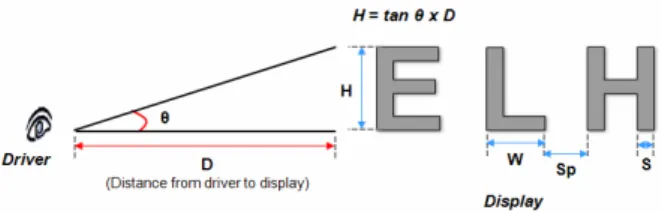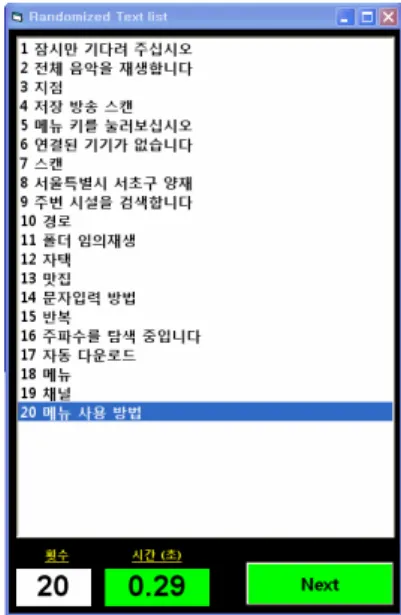
What are Legible Korean Font Sizes within In-Vehicle Information Systems?
ABSTRACT
Objective: The aim of this study is to determine legible Korean font sizes within in-vehicle information systems(IVISs) in diving conditions. Background: Font legibility within IVISs is one of important causes on its' safe operations during driving.
Several researches proposed some guidelines on the legible English font sizes within IVISs. On the contrary, appropriate Korean font sizes have been hardly known in spite of the typological differences between English and Korean. Therefore, more systematic researches for improving the legibility on Korean font size within IVISs have been required. Method: In this study, an experiment was performed with the following experimental factors: the existence of vibration, the color contrasts(white on black, black on white), the font types(HDR, CubeR, Gothic), and the font sizes(6, 8, 10, 12, 14, 16, 18, 20, 22, 24pt). To fit the experimental conditions into real driving environments, the illuminance was controlled to 15lx by using LED lamp and the distance between IVIS and participants was kept to 70cm. Moreover, all participants took the shutter glasses for employing well-known occlusion techniques. Results: The experimental results showed that 'HDR' and 'Non-vibration + Black on white' group took the shortest response time, and decreasing slopes of the response time with increasing font sizes were slowing down at 14pt then flattened out at 22pt regardless of the existence of vibration and color contrasts. Conclusion: The minimum size for legible Korean font would be about 14pt(5.47mm) and the optimum size would be about 22pt(8.59mm). Application: The guideline on the Korean font sizes from this study will be applied to design an IVIS in the future.
1. Introduction
2011년 현재 국내 내비게이션의 누적 판매량은 약 800 만 대로, 차량 등록대수 대비 약 50% 수준이라고 한다 (iNews24, 2011). 일본의 경우, 내비게이션 보급률이 전체 등록 차량 대비 80%여서 국내에서도 점점 더 보편화되리라
예상된다. 최근 보급되는 내비게이션들은 길안내 시스템뿐만 아니라 음악/동영상 재생, DMB 시청, 게임 등의 엔터테인먼 트 기능까지 갖추고 있다. 또한 이러한 기능들은 자동차 내 공조시스템이나 제어시스템과 통합되고 스마트폰과 연계되 는 추세여서 자동차 내의 정보시스템(IVIS: In-Vehicle Information System)은 점점 더 복잡해지고 있다. 이러한 복잡성 증대는 사고를 유발하는 매우 중대한 요인 중의 하나
인 운전 중 IVIS 조작의 위험성을 더욱 부각시킬 것이다.
운전 중 운전자가 얻는 피드백의 90%는 시각적인 정보이 다(Bach et al., 2009). Lee et al.(2010)에 따르면 내비게이 션 이용 중 사고에 가장 큰 영향을 끼치는 것은 아이콘과 텍 스트의 가시성이라고 한다. 즉, 아이콘과 텍스트가 눈에 잘 보이지 않으면 그 정보를 획득하기 위해 운전자의 시선이 IVIS에 오래 머물고 이는 중대한 사고로 이어질 수 있다는 것이다. 이 때문에 많은 자동차 관련 설계 가이드라인들은 운전자의 시선이 운전 외 정보에 오래 머물지 않도록 IVIS 를 설계해야 함을 강조하고 있다(ISO15005, 2002; TRL, 2002; JAMA, 2004). 운전자들은 운전 중 응시시간이 0.8 초보다 짧고, 응시 사이 간격이 3초 이내이면 안전하다고 느 낀다(Green, 1999). Zwahlen et al.(1988)은 안전 상의 이 유로 운전자들은 2초 이상 운전 태스크로부터 분산되면 안 된다는 것을 보였다. 또한, ISO15005(2002)에서는 시선이 IVIS에 머무르는 시간(도로 외 시각주의 시간, eyes-off- the-road-time)이 1.5초보다 길지 않도록 권고하고 있다.
화면 상의 시각적인 정보는 이처럼 짧은 시간 내에 운 전자에게 정확하게 전달되어야 하므로 텍스트의 가시성 (Visibility), 가독성(Legibility), 이독성(Readability)을 확 보하기 위한 노력이 IVIS 설계에서는 특히 중요하다. 가시성 은 문자나 아이콘이 주위와 구별되게 하는 성질을 의미한다.
이에 반해 가독성(legibility)이란 글자가 잘 읽히는 정도를 의미하며(Won, 2004), 글자나 단어, 기호 그리고 본문에 있 어서 타이포그래피(Typography)의 요소를 통합하고 조정 하는 것을 말한다. 일반적으로 가독성에 영향을 미치는 요인 으로는 글자체, 글자크기, 획폭, 글자/줄간격, 글자색/배경색 대비, 시야거리, 조도 등과 같이 다양하다(McLean, 1965;
Vartabedian, 1971; Vanderplas and Vanderplas, 1980;
Hwang et al., 1997; Beranard et al., 2003; Lee et al., 2007). 이독성은 문자에 의해 표현되는 단어, 문장, 문단의 정보내용을 이해 가능하게 하는 속성으로 각 문자의 글자체 보다는 자간간격, 문자의 연결, 줄간격, 여백 등의 문장구조 와 내용에 많은 영향을 받는다(Jung et al., 2006; Chae et al., 2007).
운전 중에는 운전자가 IVIS에 지속적으로 초점주의 (focused attention)를 줄 수가 없고 분산주의(divided attention)에 의존해야 하며 조도가 불연속적으로 변경되며 진동에 의한 화면 떨림이 있는 등 특히 가독성을 해칠 수 있 는 환경이다. 운전 환경에서의 적절한 가독성을 보장하기 위 해서 여러 가이드라인들에서 영문에 대한 글자크기 가이드 를 제시하고 있으나 한글에 대해서는 아직 적절한 가이드가 부족하다. 영문에 비해 한글은 획수가 많고 복잡한 구조를 갖기 때문에(Hwang et al., 1997) 적절한 가독성을 보장하 는 크기에 대한 기준이 다를 가능성이 크다. 따라서 본 연구
에서는 운전 환경에서의 적절한 가독성을 보장하기 위한 IVIS 내 한글 글자크기를 실험을 통하여 도출하였다.
2. Research Backgrounds
2.1 English font size within IVIS
Green(1999)은 IVIS 내의 글자크기에 대해 텍스트의 높 이(H)를 거리(D)로 나눈 값이 0.007보다 커야 한다(H/D
> 0.007)는 규칙을 제안하였다. '007'이라는 상수 때문에 이 가이드라인은 '제임스 본드' 규칙이라고 알려져 있다. Figure 1은 가독성에 영향을 미치는 디스플레이 상의 글자 구성요 소들과 운전자 눈과의 거리에 따른 관계를 보여준다. Table 1은 Figure 1의 각 요소들에 대해 기존 자동차 관련 대표적 인 가이드라인들이 제시하는 영문 글자크기에 대한 가이드 들을 요약한 것이다. 일반적으로 화면 상의 정적이고 중요하 지 않은 정보의 글자표시 높이(H)는 최소 3.1mm보다 커야 함을 제안하고 있으며, 차량 내에서와 같이 움직임과 떨림이 있는 경우 가독성이 감소하기 때문에 글자의 높이는 최소 4.9mm보다 커야 함을 추천하고 있다(ISO15008, 2003;
TRL, 2002). 또한 보다 중요하고 긴급한 정보는 6.6mm보 다 더 크게 보여주는 것이 좋다(UMTRI, 1994).
Table 1에서 보여주듯이, 적절한 글자의 크기는 운전자 눈과의 거리, 진동 여부(떨림), 정보의 움직임 특성(정적/동 적)에 따라 달라진다. 또한 약한 조명과 색조, 컬러대비가 가독성을 떨어뜨릴 가능성이 있다면 글자크기는 더 커져야 한다. 자동차 환경에서의 적절한 글자크기를 결정하기 위해 서는 이러한 특성들이 고려되어야 할 것이다.
Table 1을 보면, 글자의 크기를 구성하는 글자폭(W), 획 폭(S), 글자간격(Sp) 등의 요소들은 글자높이(H)에 의해 비례적으로 결정될 수 있음을 알 수 있다. 높이(H)만 결정 되면 그 외의 요소들은 이 가이드라인들을 참고하여 정의할 수 있으므로 본 연구는 우선적으로 높이를 기준으로 적절한 글자크기를 결정하였다.